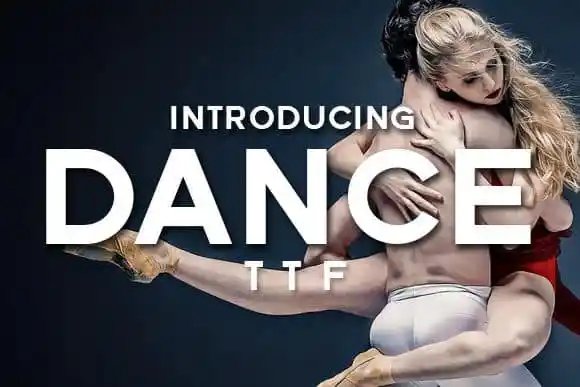
Dance Sans Serif Font – Download Grátis
A Dance Sans Serif Font é uma escolha perfeita para seus logotipos em maiúsculas iniciais ou qualquer projeto que exigir possa uma tipografia leve e poderosa. Desenhada pelo designer vladimirnikolic, ela se tornou um recurso versátil no mundo da criação visual. Seja em camisetas, cartazes ou folhetos, a Dance Sans Serif tem o dom de tornar seu trabalho mais chamativo. Suas linhas simples e limpas criam uma identidade visual moderna que atinge os olhos de qualquer um que a veja. Experimente adicioná-la aos seus projetos mais criativos, e você verá como ela transforma suas ideias em algo realmente especial. Esta font será definitivamente o seu novo favorito para qualquer projeto design que precise de uma sensação leve e moderna.